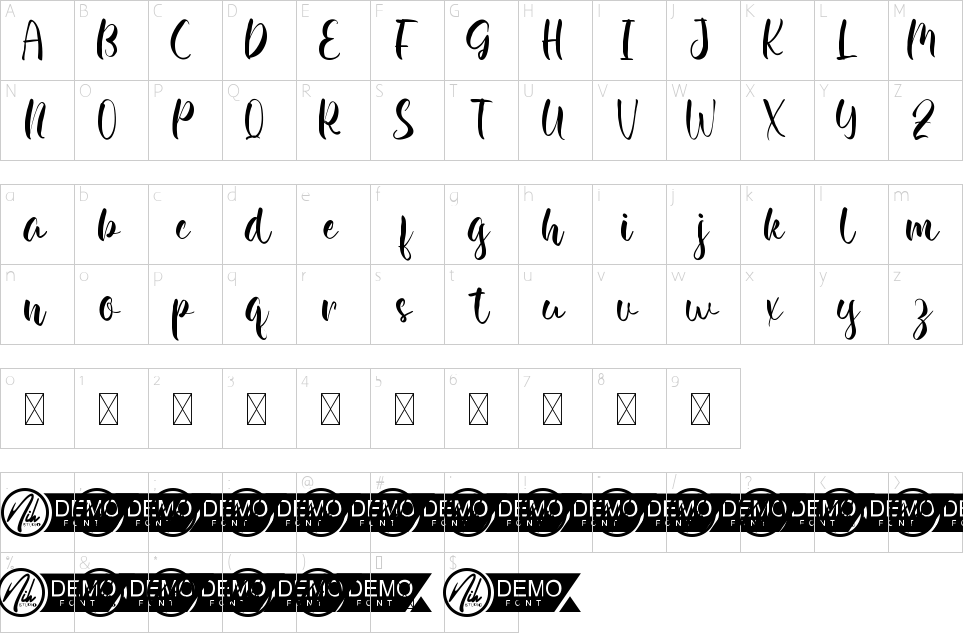
Aqui está uma descrição envolvente para a página de download da font ‘Gorgeous Brush Font – 1001 Free Fonts’: Descubra a beleza elegante e sofisticada das fontes brush neste vasto repositório gratuito. A font Gorgeous Brush é um verdadeiro prazer visual, ideal para dar um toque especial em seus projetos digitais. Ela foi criada com cuidado por nihstudio, uma equipe talentosa que busca criar soluções de design inovadoras. Este rico conjunto de 1001 free fonts inclui Gorgeous Brush, garantindo uma ampla variedade para atender todos os seus requisitos de design. Para usuários do Windows e Mac, o Gorgeous Brush está disponível gratuitamente aqui. Esta font é especialmente adequada para nomes de produto, títulos de página ou qualquer outro elemento que exija um toque elegante e sofisticado. Se você procura uma maneira fácil e rápida de dar um up no visual de seus projetos digitais, Gorgeous Brush pode ser a solução perfeita. Com uma variedade imensa de fonts gratuitas disponíveis para download, o site 1001 Free Fonts é sua fonte confiável para encontrar recursos design da melhor qualidade sem compromissos. Para aqueles que buscam a máxima elegância e sofisticação em suas criações digitais, Gorgeous Brush é uma escolha perfeita.